НЕБРЕЖЕН РЪКОПИС
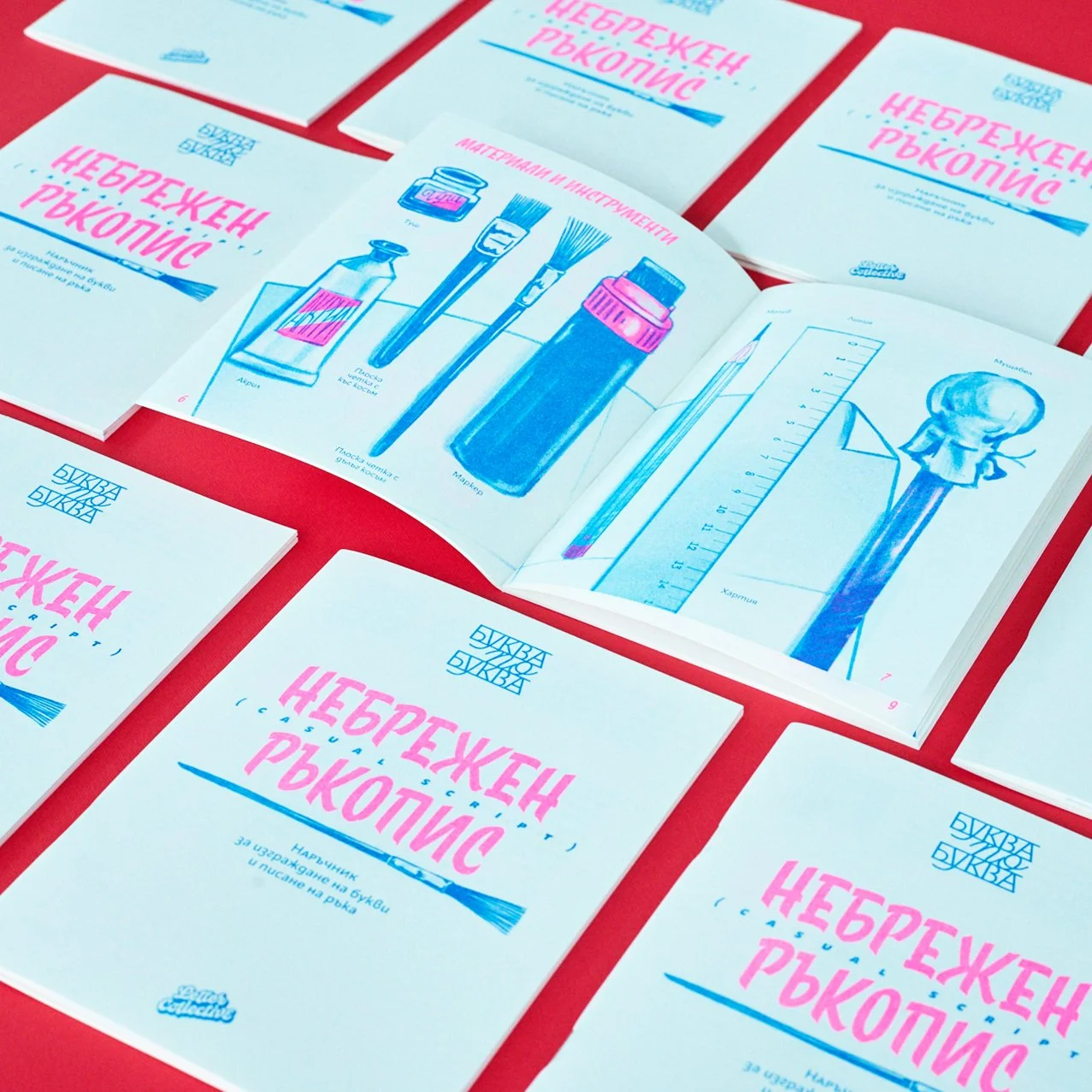
Наръчник за изграждане на букви и писане на ръка. Първото издание се фокусира върху типичния стил на Небрежния ръкопис (Casual script). Включва раздели, даващи информация от калиграфска и шрифтова гледна точка – терминология, анатомия, инструменти, технически параметри и пр., както и стъпка по стъпка изписването на буквите от Латиницата и Кирилицата.